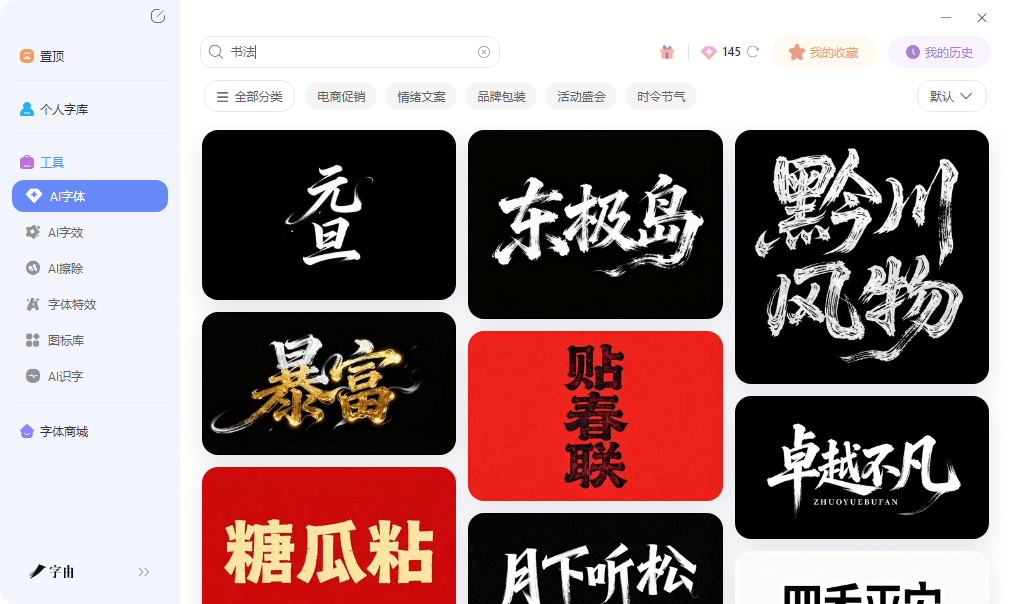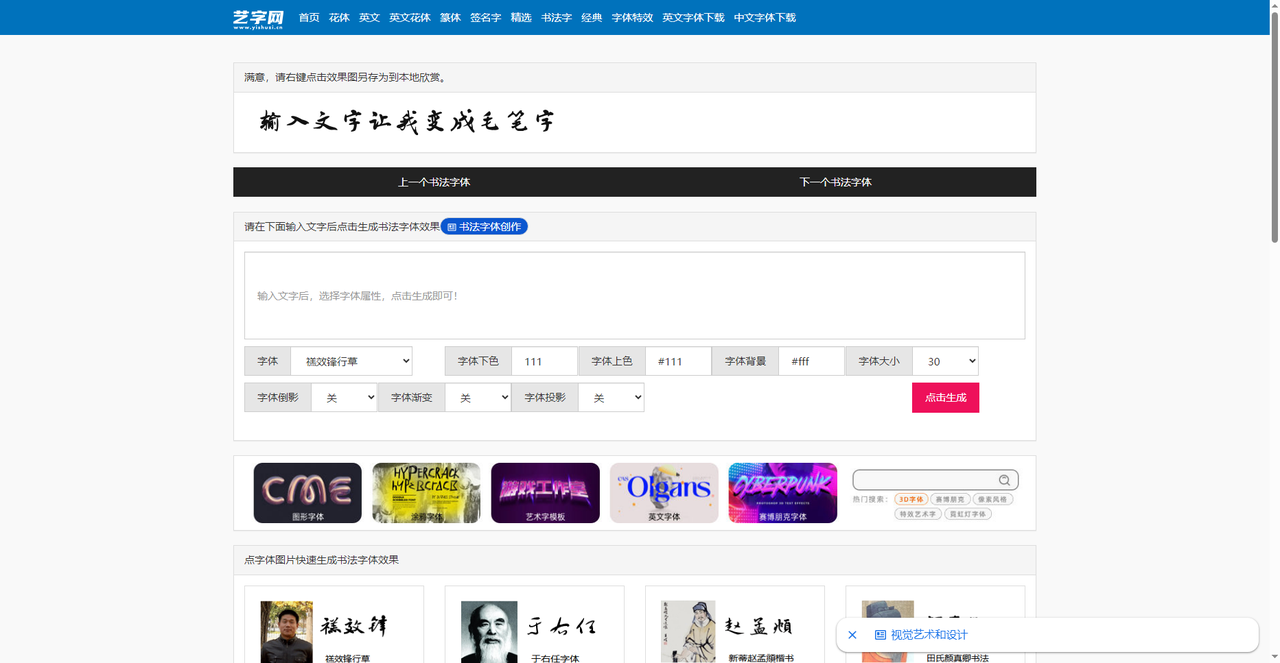
免费生成书法字体,几个网站直接搞定
做中式海报时,书法字体是提升设计感的关键元素,现在有不少在线工具可以支持在线生成书法字体:有的提供正版书法字体一键激活,有的支持输入文字直接生成书法效果图,还有的收录了大量书法字体资源供免费下载。这篇文章推荐了5款书法字体相关的工具,覆盖了从在线生成到字体安装的多种使用方式。
字由的字体库中专门设有书法体分类。用户打开字由客户端,在左侧筛选栏的字体类型中勾选书法体,系统列出所有书法风格的字体。这些字体涵盖了楷书、行书、草书、隶书、篆书等主要书体,总计数百款。每款字体都标注了使用热度,热度数据基于平台上所有设计师的真实使用次数统计。
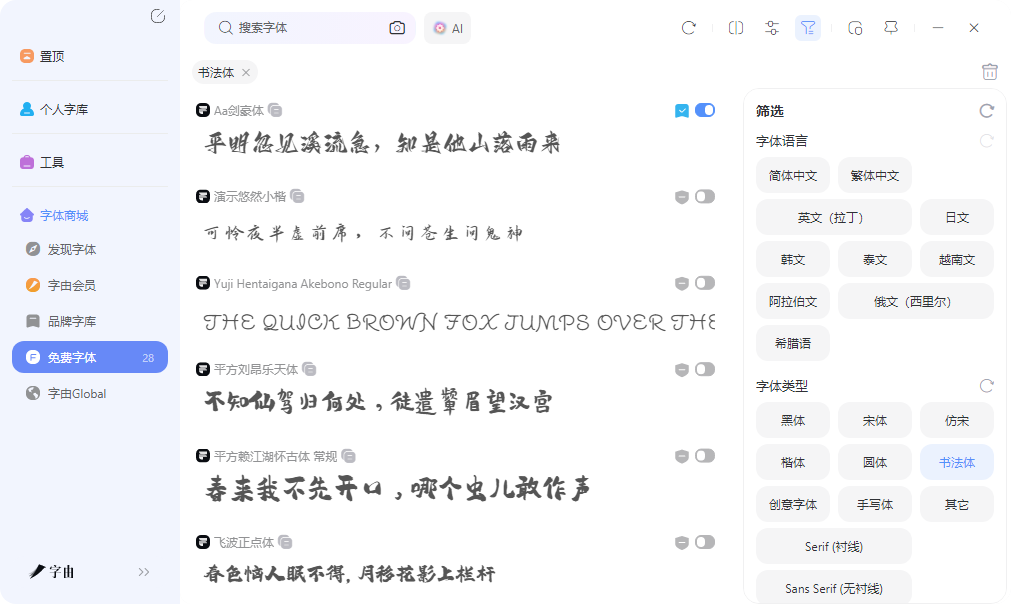
不熟悉书法字体的用户,可以按热度从高到低排序。排在前面的字体通常是大多数设计师验证过的,笔画清晰、连笔自然、整体识别度高。需要小众风格的用户可以按热度从低到高排序来寻找。
除此之外用户也可以选择使用AI字体来生成,里面积累了大量关于书法字体的现成模板,只需要不到一分钟就可以拿到一份已经渲染好的书法字体图片,也可以选择保存为透明底格式方便用在PS 等设计软件里,而且也是几乎完全免费的,每天签到会送6个算力点,生成一张只需要3算力点。
2、艺学网
第二个网站是艺学网的书法字体在线生成板块。用户输入文字后,可以选择不同的毛笔字体(如斌纹锋行草),调节字体下色、上色、背景颜色、字体大小,还可以打开或关闭字体倒影、渐变、投影等特效,点击生成按钮即可输出书法效果图片。倒影效果让文字产生水面倒影的视觉;渐变效果让文字颜色从一种过渡到另一种;投影效果为文字添加阴影。这些特效都可以通过开关控制,不需要用户手动调节参数。生成后用户可右键点击图片另存为到本地。适合需要快速输出单张书法字图片、不需要长期保存字体的场景。
3、CND设计网
第三个网站是CND设计网。它是一个设计作品分享平台,收录了大量字体设计作品,其中包含众多书法字体的创意应用案例。用户可以在搜索框中输入关键词,查找相关字体设计灵感。该网站收录了44021张字体作品,用户可以按最新发布、热门推荐等排序浏览。优秀字体设计师榜单展示了活跃设计师的代表作品,用户可以参考其字体设计风格。该网站主要用于获取设计灵感,而非直接生成或下载字体。用户看到喜欢的字体样式后,可以记下字体名称,再到字由或其他平台搜索该字体并激活使用。
4、395工具
第四个网站是395工具。它整合了多个书法相关的在线资源,用户可以在一个页面中访问书法迷字典、名家书法集、五体书法字典、篆刻字典、书法家字库等27个书法工具。书法迷字典用于查询单个汉字的多种书法写法;五体书法字典涵盖草行楷隶篆五种书体;篆刻之家和印章生成用于制作篆刻效果;花鸟字生成用于装饰性文字。这些入口覆盖了从字体查询到印章制作的完整需求。用户需要查找某个汉字的特定书法写法时,可以通过书法迷字典快速定位。需要制作印章效果时,可以使用印章生成工具。该网站将分散在不同平台的书法工具集中在一起,节省了用户逐个搜索的时间。
5、字体家
五款工具各有侧重,字由适合需要在PS中长期使用同一款书法字体的设计师,一键激活即可调用,支持多设备同步。艺学网适合临时输出单张书法字图片,支持倒影渐变等特效调节。CND设计网提供字体设计灵感参考,适合寻找搭配方案。395工具整合了27个书法资源入口,适合查询单字写法或制作印章效果。字体家拥有上万款中文字体的下载资源,免费商用专区授权清晰,适合需要下载字体文件到本地的用户。根据自己需求选一个就行。